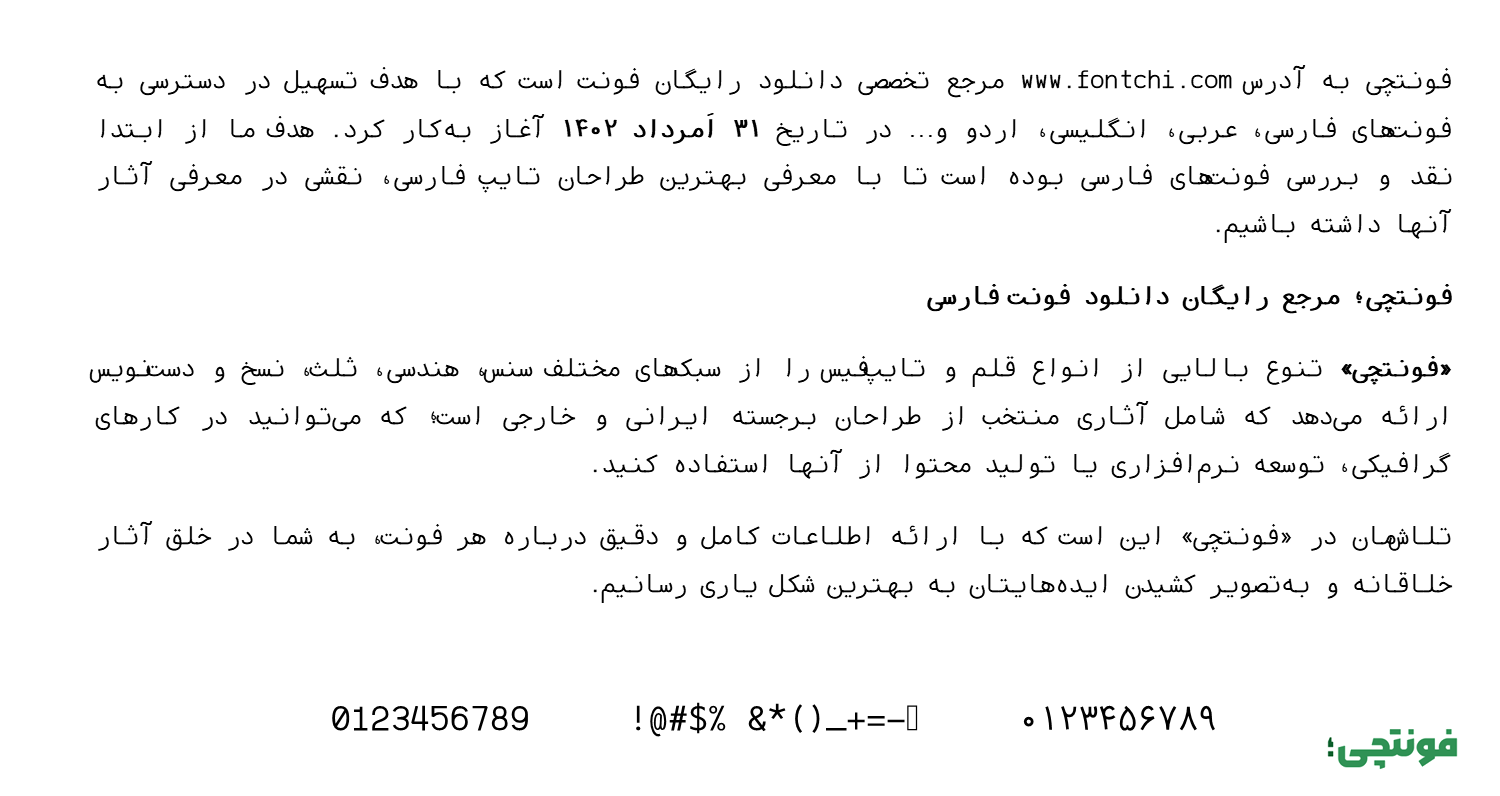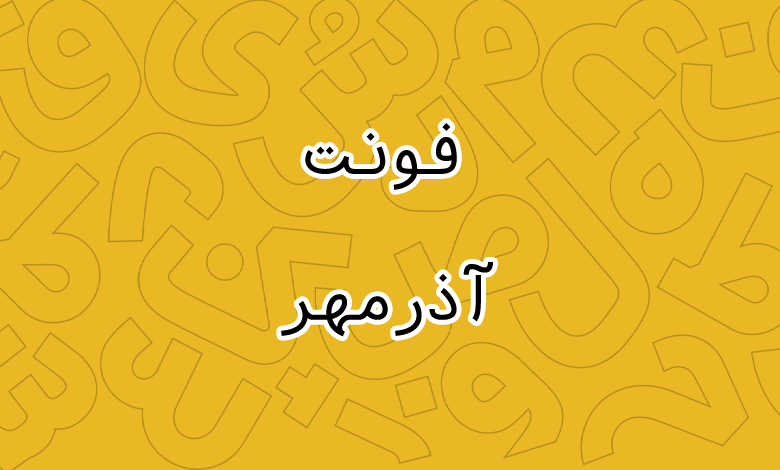
فونت آذرمهر (Azarmehr)
فونت آذرمهر (به انگلیسی: Azarmehr) قلمی به سبک خط سنس با کنتراست پایین است. در این تایپفیس سعی شده تا با داشتن دورهای بیشتر، از شکستگیها کاسته شود. از همینرو فونت دارای ظاهری صمیمی و دوستانه است. لازم به ذکر است که فونت آذرمهر رایگان نیست و نسخهای که در اینجا برای شما آماده کردهایم شامل نسخه مونواسپیس این قلم است.
بررسی و دانلود فونت آذرمهر رایگان (Azarmehr)
فونت آذرمهر توسط امین عابدی در یک سبک سنس طراحی شده است. وی سابقه همکاری با طراحان گرافیک متعددی را دارد که فونتهای موفقی هستند.
فونت آذرمهر از زبانهای فارسی، عربی، انگلیسی پشتیبانی میکند. در نسخه مونواسپیس این قلم که شامل فونتی با حروف همعرض میشود (یعنی تمامی کاراکترهای فونت دارای عرض یکسانی هستند)، دو وزن معمولی Regular و ضخیم Bold پشتیبانی میشود.
از این قلم میتوانید در متون کوتاه تا بلند استفاده کنید، هرچند که برای متون کوتاه و عناوین توصیه میشود حتما نسخه تجاری آن را خریداری کنید که شامل وزنهای ضخیمتر همچون ExtraBlack است. از نسخه مونو اسپیس میتوانید در حوزه چاپ همچون روزنامه، مجلات و آگهیها استفاده کنید که ظاهر خوانایی دارد.
این قلم برای استفاده در متون طولانی گزینهای عالی محسوب میشود که موجب خستگی چشم نخواهد شد. در تمامی زبانها همآهنگی بین گلیفها رعایت شده است. کاراکترهای خاص هر زبان همچون اعراب نیز در همنشینی صحیحی با حروف قرار میگیرند.
این فونت همچنین از اعداد فارسی پشتیبانی میکند که بسته به نوع زبان صفحه کلید، در صورت عربی بودن اعداد استاندارد عربی بهصورت «۰۴۵۶» تایپ خواهد شد.